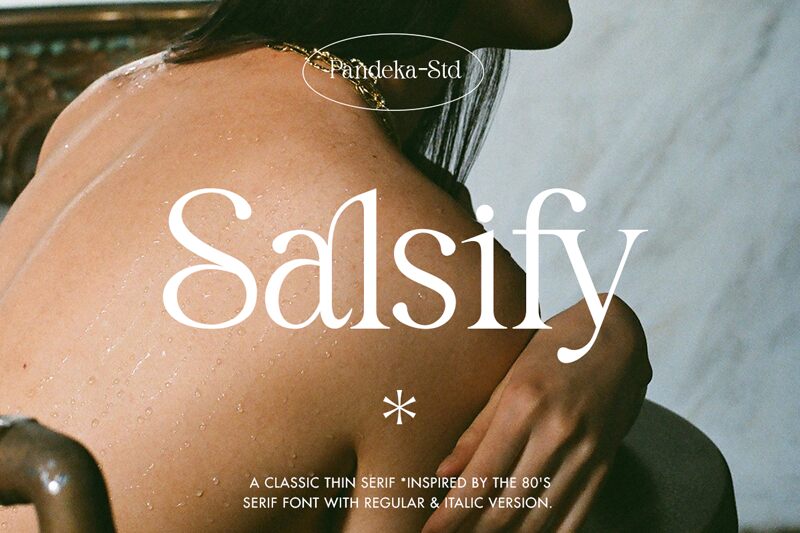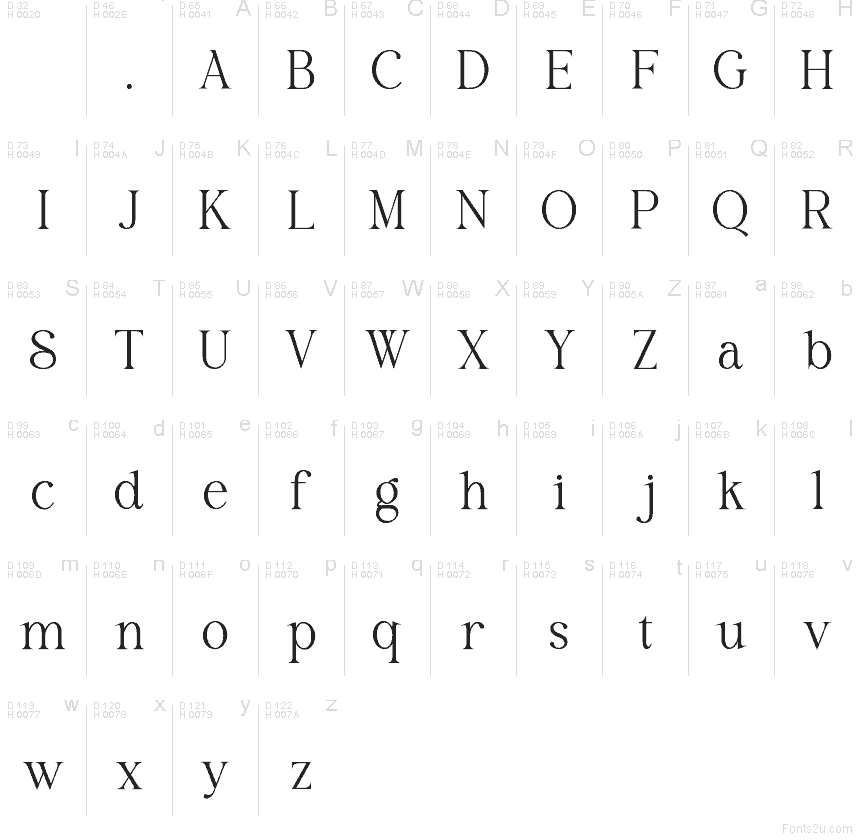
Salsify od Pandeka Studio je bezplatné patkové písmo s vysokým kontrastem, které má nádech módních redakčních materiálů. Písmena spojují tenké vlásenkové tahy s širokými, klenutými křivkami a díky nadměrně velkému počátečnímu S působí písmo vyváženě, jemně a trochu dramaticky, aniž by bylo přehnaně zdobné.
Hodí se pro záhlaví časopisů, obaly kosmetiky, branding butiků, knižní obálky i vytříbenou grafiku s citáty, kde kontrast dokáže zapůsobit jen několika znaky. Jako bezplatný font funguje skvěle také pro titulky a krátké texty, zejména pokud hledáte něco půvabného a lehce formálního, co však nepůsobí stroze.